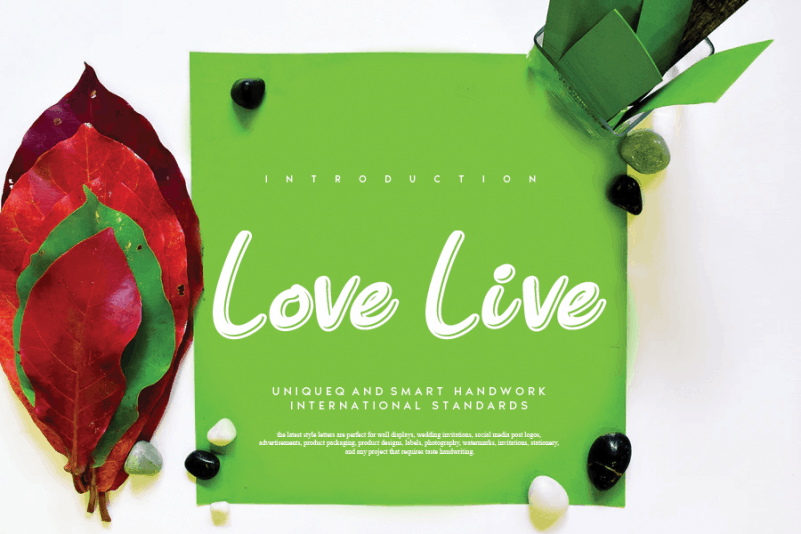
Love Live Display Font – Fonte Grátis
Love Live Display Font
A Love Live Display Font é uma elegante fonte escrita a mão que transmite sensações envolventes de criatividade e harmonia. Inspirada na fidelidade do estilo, essa fonte fluida convida projetistas a cair de amores por sua aparência singular e eterna. Usar essa fonte é uma maneira fascinante para criar designs impressionantes que capturam a essência da arte do desenho à mão, tornando-a não apenas um recurso gráfico útil, mas também uma extensão do seu próprio estilo criativo.